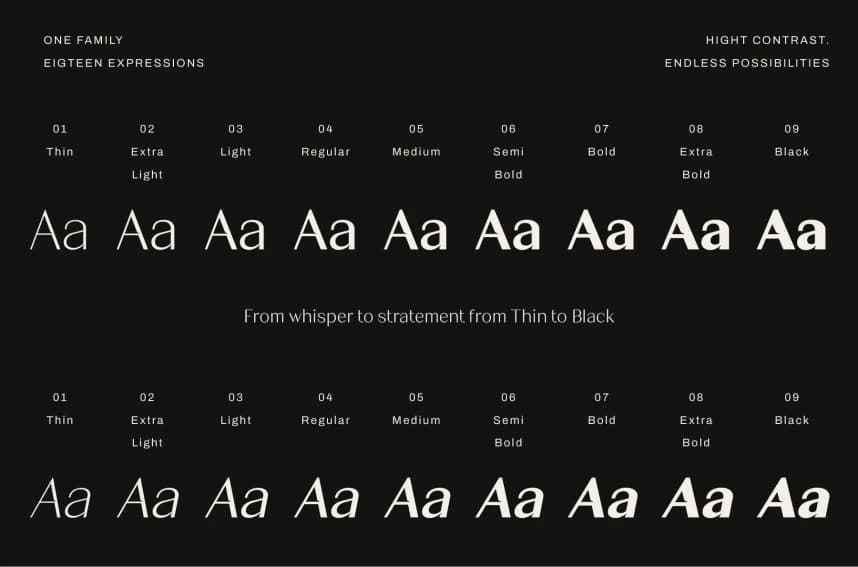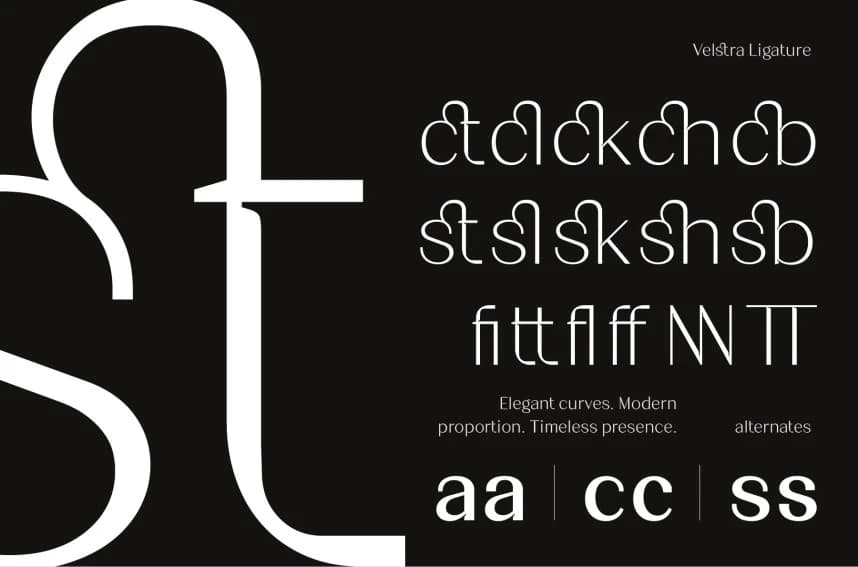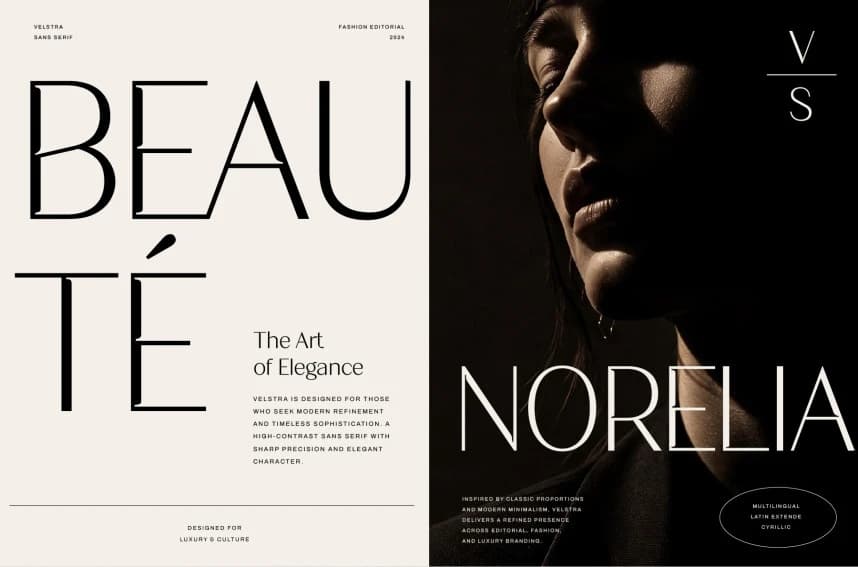
Velstra Yazı Tipi
Velstra Font, profesyonel tasarım projelerine zarafet, netlik ve modern bir etki kazandırmak üzere tasarlanmış yüksek kontrastlı bir sans-serif yazı tipi ailesidir. Dik (upright) ve eğik de dahil olmak üzere 18 stile sahip olan Velstra, İnce'den Kalın'a kadar değişen bir aralığa sahiptir ve tamamen
Velstra Font, profesyonel tasarım projelerine zarafet, açıklık ve modern etki kazandırmak için tasarlanmış yüksek kontrastlı sans-serif bir yazı tipi ailesidir. Düz ve eğik dahil olmak üzere 18 stile sahip olan, İnce'den Kalın'a kadar değişen ve tamamen esnek bir Variable Font ile Velstra, her görsel yön için tam yaratıcı özgürlük sunar.